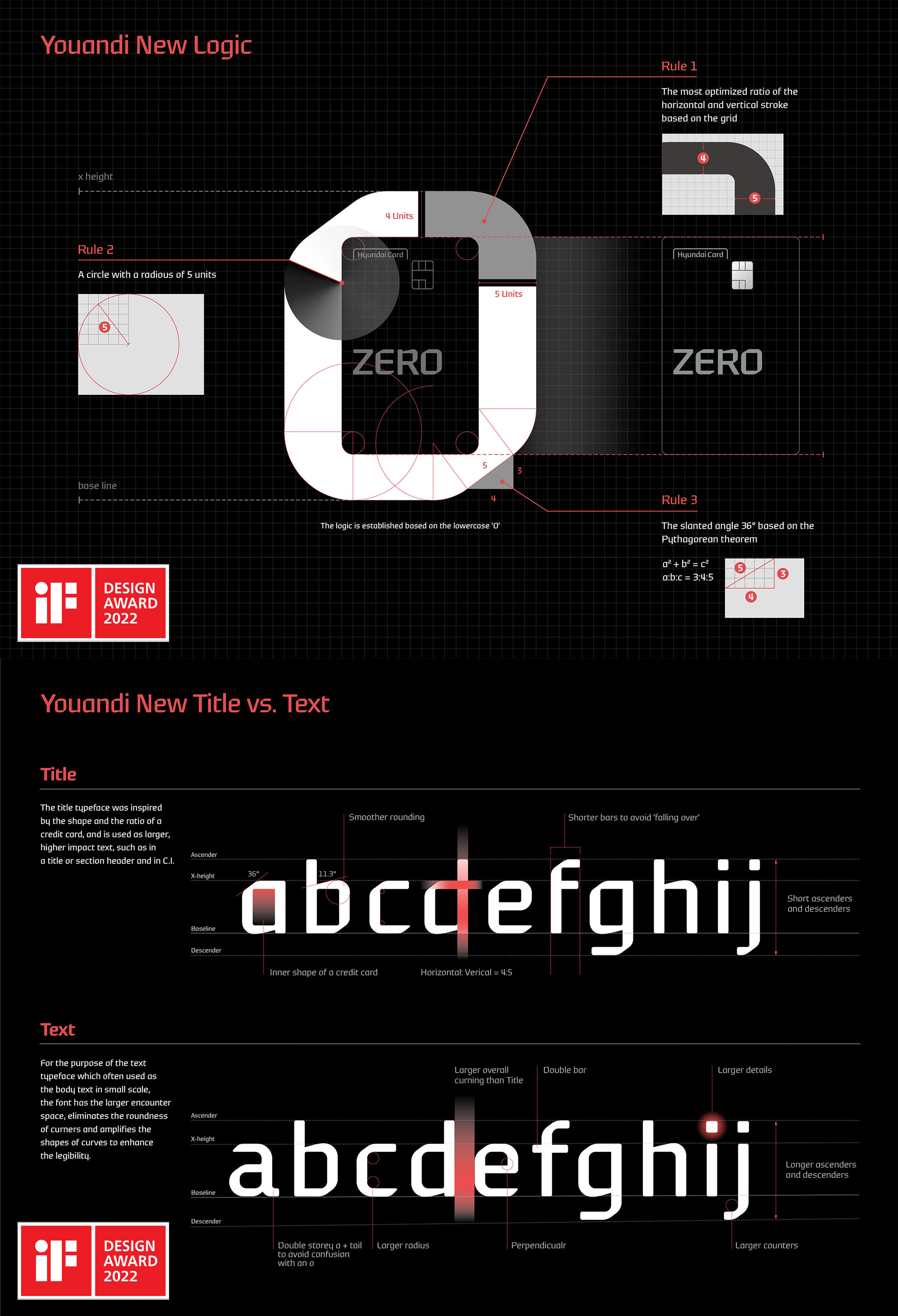
‘iF 디자인 어워드 2022’를 수상한 ㈜윤디자인그룹의 '유앤아이뉴'체 (사진제공:현대카드)
‘유앤아이뉴’체를 적용한 카드 플레이트 디자인 (사진제공:현대카드)
커뮤니케이션(Communication) 부문에서 본상을 수상한 ‘유앤아이뉴(Youandi New)’는 현대카드가 지난 2003년 국내 최초로 공개한 기업 서체인 ‘유앤아이(Youandi)’를 리뉴얼한 버전으로 다양한 매체에 최적화 해 적용할 수 있는 무한한 확장성이 특징이다. 국내 기업 서체 최초로 굵기와 기울기, 너비 등을 임의로 조절할 수 있는 가변서체(Variable Font)로 제작된 유앤아이뉴는 표현 가능한 서체 종류가 12만 5360자에 달한다. 현대카드는 ‘the Purple osée’ ‘the Pink’ ‘MX Black’ 등 지난해 출시한 신상품의 카드 플레이트 디자인과 패키지에 유앤아이뉴를
적용한 바 있다.